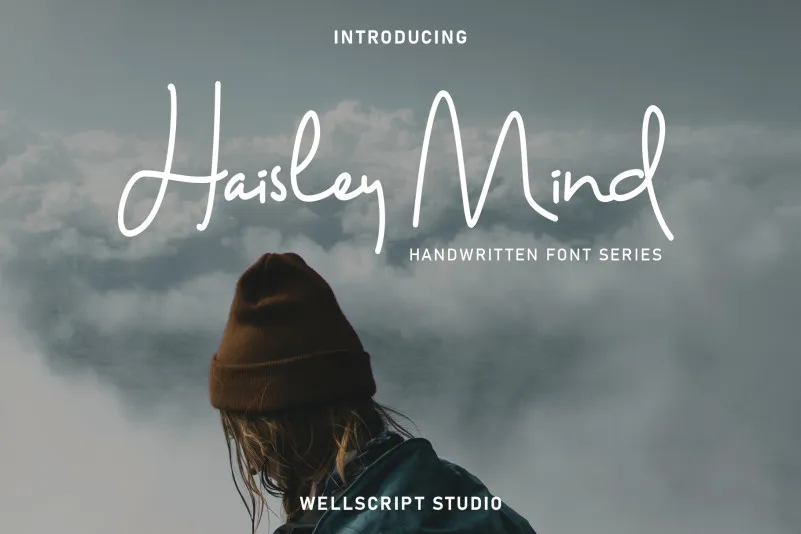
Haisley Mind – Handwritten Script Font – Download Grátis
A Haisley Mind é uma fonte script escrita a mão que traz consigo uma atmosfera envolvente e natural perfeita para quem busca um toque delicado e único. Com seu design elegante e linhas simples, essa fonte adquire uma aparência orgânica e fresca que se destaca em qualquer projeto gráfico. Ideal para aplicar em elementos românticos como datas de aniversário, embalagens ou convites de casamento, a Haisley Mind também é perfeita para branding personalizado. Combinada com uma paleta de cores suaves e delicadas, essa fonte pode criar um design único e memorável que se encaixa perfeitamente em diversos contextos. Seja para projetos íntimos ou corporativos, a Haisley Mind é certamente uma escolha ideal para quem busca aquela nota especial em seus materiais impressos.